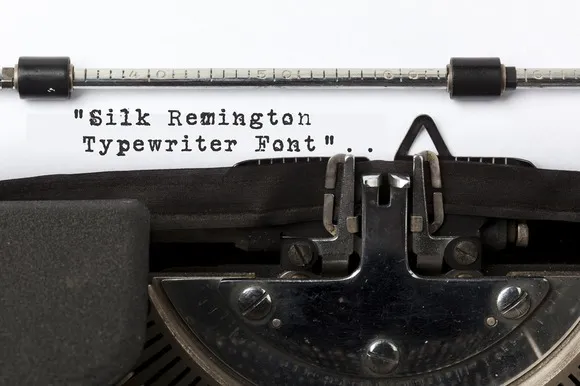
Silk Remington SBold Font – Download Grátis
A Silk Remington SBold Font é uma elegante opção para quem busca um estilo retrô no seu design digital. Inspirada nos typewriters vintage, essa fonte oferece um contraste arquitetônico e clássico que combina bem com diferentes formatos de texto. Seja você um designer gráfico ou simplesmente alguém que adora explorar diferentes estilos digitais, esta fonte é perfeita para uma experiência única e encantadora. A Jadugar Design Studio é conhecida por produzir designs únicos e incríveis, e Silk Remington SBold Font é mais uma prova disso. Com seus 5 estilos completos disponíveis na Creative Market, você pode experimentar tudo o que a Jadugar tem a oferecer. Se você está procurando um upgrade para seu design digital, esta fonte certamente vai deixá-lo impressionado com seu charme e personalidade única.